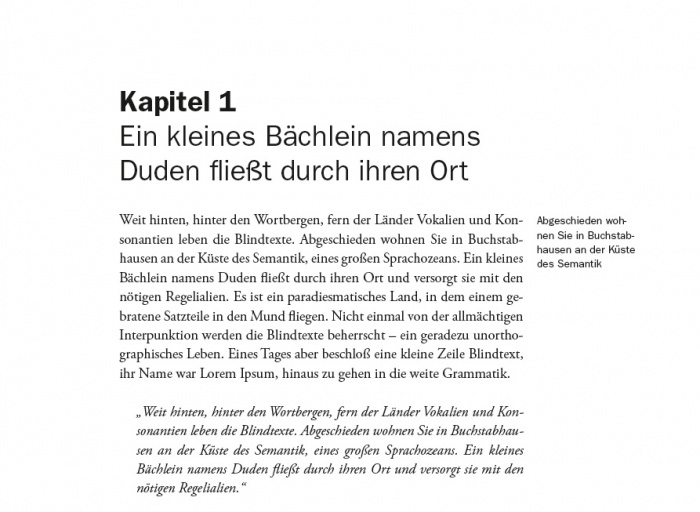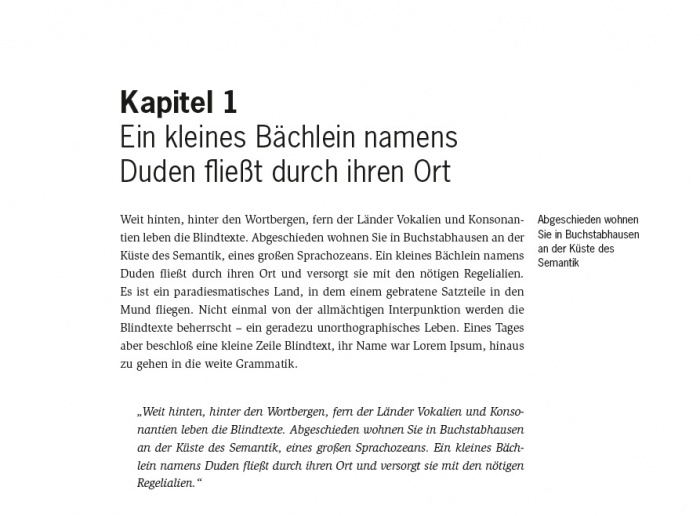
Schriftkombination für wissenschaftliche Aarbeit (Slimbach/News, Garamond/Franklin Gothic)
ich denke zurzeit darüber nach, wie das typografische Erscheinungsbild meiner wissenschaftlichen Arbeit (im MINT-Bereich) sein soll. Eine Arbeit in der Vergangenheit hatte ich mit Minion/Franklin Gothic erstellt. Ich bin nach wie vor ein großer Fan der Franklin Gothic. Ich wollte etwas anderes probieren und habe zwei Kombi-Möglichkeiten erarbeitet:
1. Bild: ITC Slimbach und News Gothic - Meinung?
2. Bild: Adobe Garamond Pro und ITC Franklin Gothic - Meinung?
Welche serifenlose Schrift eignet sich (außerdem) für die Slimbach? Könnte man auch Slimbach und Franklin kombinieren? Die Slimbach hat ein sauberes und neutrales Erscheinungsbild, ich mag die X-Höhe der Buchstaben. Allerdings hebt sich hier die Kursivschrift nicht so sehr ab, wie bei der Garamond. Die Garamond hat für mich eher ein Romanbuch-Charakter, aber die Kursivschrift ist gut. Als Alternative zur Garamond sehe ich noch Warnock, diese gefällt mir immer mehr und könnte sich zum Favoriten entwickeln.
Was meint ihr würde besser zum Thema passen (MINT = Mathematik, Informatik, Naturwissenschaft und Technik). Habt ihr vielleicht noch bessere Kombinationsvorschläge?
Ich habe einige naturwissenschaftliche Arbeiten in der Garamond korrigiert. Insgesamt finde ich sie immer zu literarisch. Die Minion ist da für mich ein guter Mittelweg. Mit der Slimbach habe ich selber nie gearbeitet, aber ich bin irgendwann mal über ein Journal gestolpert welches sie verwendet. Falsch machste damit nix. Die Warnock habe ich selber öfters mal als Fließtextschrift für Posterpräsentationen verwendet. Dafür hat sie mir gut gefallen und ich habe sehr gerne damit gearbeitet. In größeren Graden finde ich sie allerdings etwas zu eigenwillig, aber in Fließtextgrößen funktioniert sie gut.
Was eine serifenlose Alternative angeht: ich habe in letzter Zeit öfter mal die CamingoDos Semicondensed mit der Minion kombiniert und finde eigentlich daß das sehr gut geht. Mit der CamingoDos läßt sich sehr gut arbeiten. Allerdings ist sie nicht ganz billig.
Wenn Du ein paar Euro investieren kannst und Serifenlose ähnlich amerikanischer Groteskschriften magst: FF Good und FF More lassen sich wunderbar kombinieren. Außerdem hast Du eine gute Auswahl von Schriftweiten und -gewichten, welche Du für Deine Arbeit für geeignet hältst. Inwiefern der Zeichenvorrat aber Deinen Anforderungen entspricht, solltest Du vorher noch mal in der Zeichentabelle prüfen. Die Minion mit über 1.600 Glyphen ist da ja schon ein gewisser Primus. Die Pro-Versionen scheinen mir aber schon ausreichend reichhaltig zu sein. ; ) Ich denke, mit diesen beiden erwirbst Du zeitgemäße und unverbrauchte Qualitätsschriften an denen Du sehr lang Deine Freude haben wirst.
Etwas kostengünstiger aber dennoch recht üppig ausgestattet wäre die Trivia-Sippe. In Deinem Fall könnte man zum Beispiel die Trivia Grotesk mit der klassizistischen Trivia Serif 10 (für Mengensatz optimiert) kombinieren.
Andernfalls könntest Du Dir auch einmal die beiden kostenfreien Schriftsippen PT Sans/Serif und Droid Sans/Serif zu Gemüte führen. Die sind leicht eckig ausgespannt und würden daher sicher auch gut zu einem technischen Thema passen.
Die Slimbach finde ich für Deine Zwecke nicht so geeignet, weil das g aufgrund seiner ungewöhnlich großen Schlaufe viel Aufmerksamkeit auf sich zieht und damit vom Inhalt ablenkt. Die Garamond wäre mir auch zu »literarisch-poesievoll«.
Mit welchem Programm setzt Du eigentlich Deine Arbeit? Das Kerning (Buchstabenabstände) insbesondere bei der News Gothic ist ja leider nicht so doll.
Mit InDesign. Das Kerning liegt an dem Font. Trade Gothic ist da noch schlimmer (Beispiel: "ab", "Ju"). Die News Gothic ist etwas besser beim Kerning, aber nicht perfekt.
eine besser gekernte verwandte der amerikanischen grotesken:
http://www.lucasfonts.com/fonts/spiegel/
die meisten garamonds finde ich auch zu literarisch für naturwissenschaftliche themen. die minion geht natürlich immer. generell könnte ich mir etwas stabileres – vielleicht sogar eine slab – ganz gut vorstellen. möglich wären zum beispiel:
1) cambria (microsoft cleartype-schrift): http://i33.tinypic.com/2qjayi0.png
2) pt serif (kostenlos): http://i34.tinypic.com/viphxz.png
3) warnock: http://oi34.tinypic.com/w2ce9l.jpg
PT Serif und PT Sans (http://www.paratype.com/public/) sind wirklich eine starke Kombination, habe ich bereits getestet. Das Erscheinungsbild ist alles andere als literarisch. Die Schriften sind sehr gut lesbar - eine runde Sache. Gefällt mir. Eigentlich ideal für wissenschaftliche Arbeiten - und dazu noch gratis.
Droid Serif und Droid Sans sind ähnlich. Die Droid Serif ist etwas kantiger/technischer (Droid'ig eben ;-)). Allerdings handelt es sich hier eigentlich um eine für mobile Endgeräte optimierte Schrift bzw. um eine Display-Schrift. Ich vermute, das PT-Paar ist technisch für Printprodukte besser ausgereift - Paratype ist schließlich nicht irgendwer.
Ansonsten behalte ich noch die Warnock im Hinterkopf (Was ist mit Palatino? - wirkt noch etwas "sauberer"). Über alle Ansätze muss ich nochmal reflektieren.
PT Serif + Source Sans Pro sowie Warnock oder Slimbach + Frankling Gothic zähle ich momentan zu meinem Typo-Repertoire im wissenschaftlichen Bereich. Ich habe bisher viel herumexperimentiert und tue dies auch immernoch. Meine Erfahrungen will ich hier lediglich auch für andere bereitstellen - Trial and Error. Und Meinungen mit anderen austauschen...